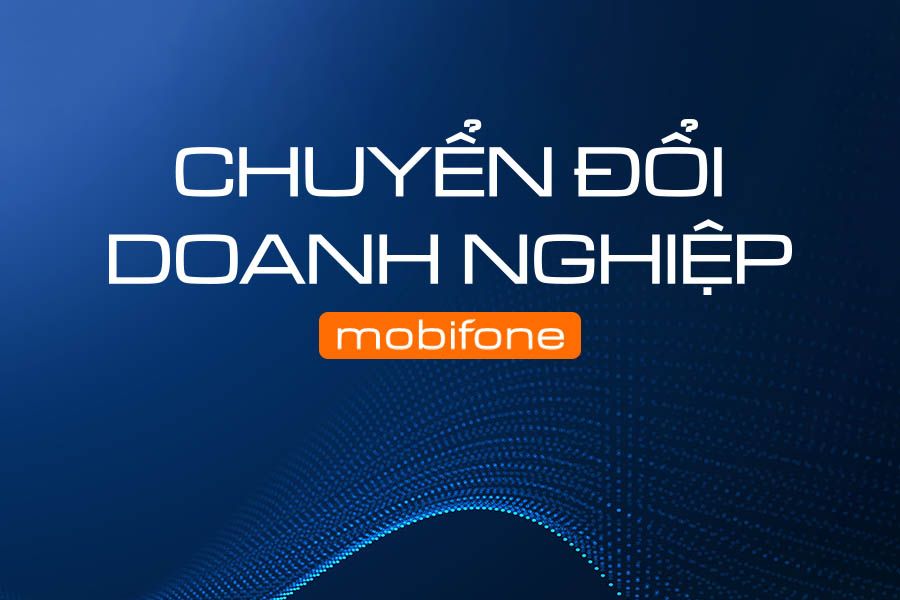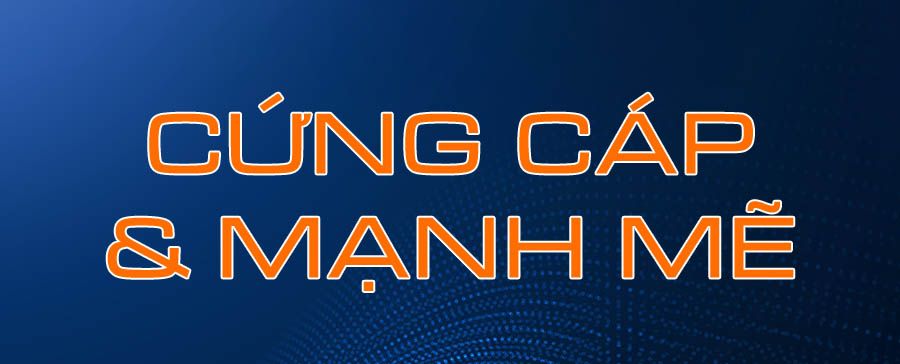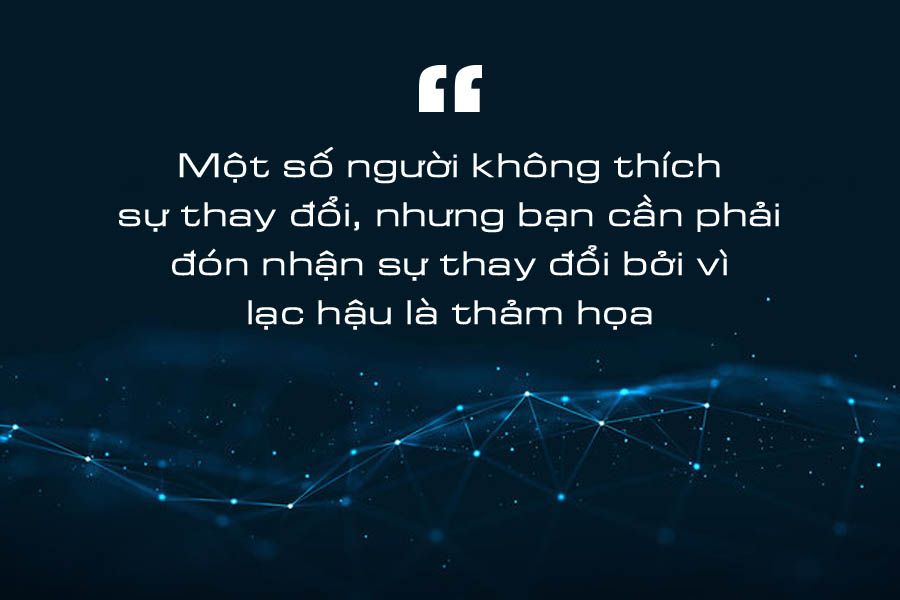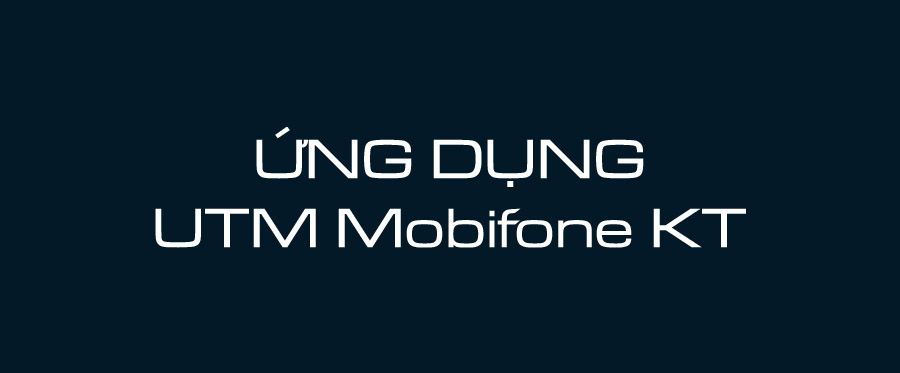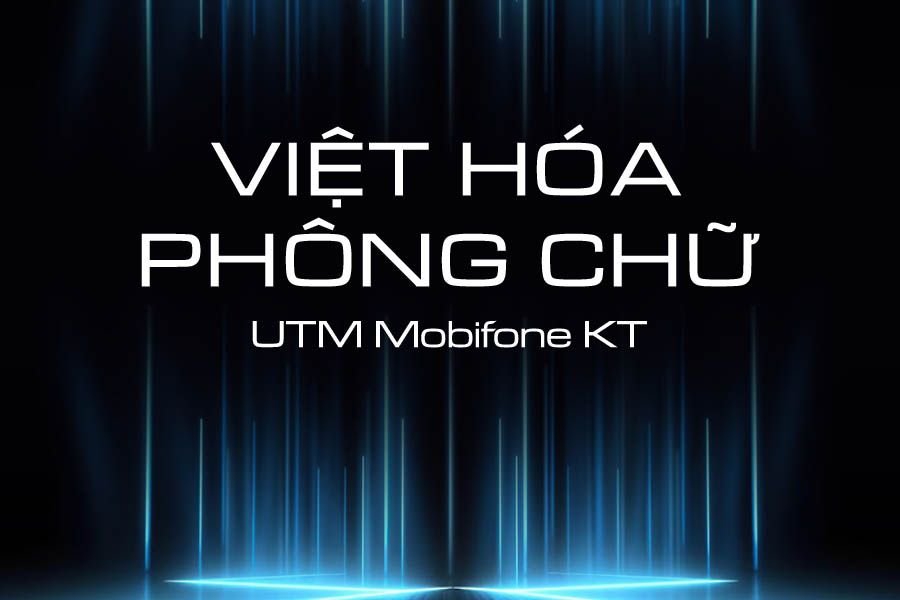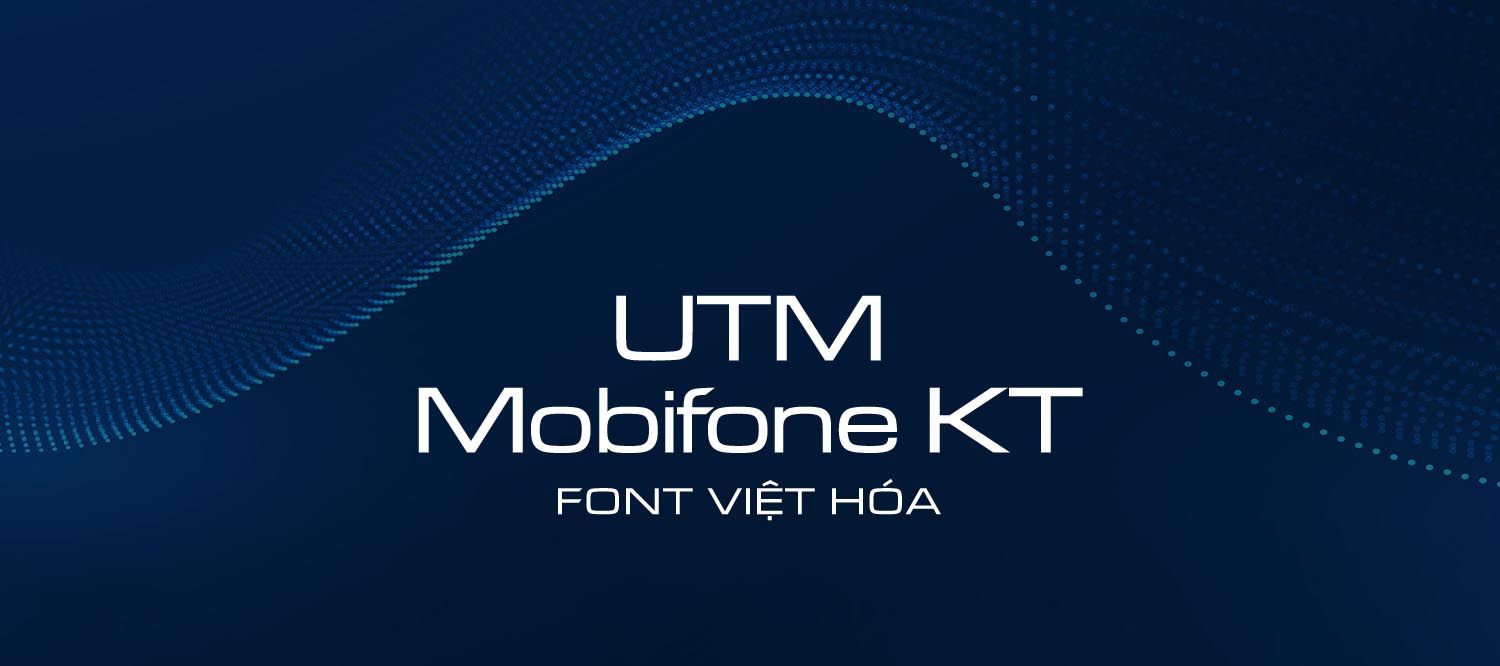
![[Tải Xuống] Font UTM Mobifone KT Cứng Cáp, Mạnh Mẽ & Hiện Đại](https://cdn.s99.vn//cloud/TCaD8aATd7PT8Ugo.jpeg)
Font UTM Mobifone KT là một kiểu chữ không chân (sans-serif) hiện đại, được Việt hóa bởi nhóm Urban Type Management (UTM) – đơn vị tiên phong trong việc Việt hóa font cho thương hiệu tại Việt Nam. Đây là bộ font từng xuất hiện trong bộ nhận diện của Mobifone, thể hiện tinh thần cứng cáp, mạnh mẽ và chuyên nghiệp – đúng với hình ảnh mà một tập đoàn viễn thông lớn muốn truyền tải.
Font UTM Mobifone KT sở hữu cấu trúc chữ không chân, mang đậm tính hiện đại và tối giản. Tuy nhiên, điều làm nên khác biệt chính là độ cứng cáp trong từng đường nét – các ký tự vuông vức, chắc chắn, không rườm rà nhưng vẫn dễ nhìn và đầy tính nhận diện. Sự mạnh mẽ này khiến font trở nên lý tưởng cho các thương hiệu công nghệ, tài chính, viễn thông và doanh nghiệp chuyên nghiệp.
Nhờ thiết kế hài hòa về khoảng cách chữ và tỷ lệ chiều cao, font UTM Mobifone KT luôn giữ được sự rõ ràng, sắc nét dù sử dụng trên màn hình số hay bản in. Dù là tiêu đề lớn hay body text nhỏ, font vẫn mang lại cảm giác dễ đọc, không bị vỡ chữ hay gây rối mắt.
Bộ font được Việt hóa hoàn chỉnh, hỗ trợ đầy đủ dấu và ký tự đặc biệt trong tiếng Việt. Các dấu thanh được thiết kế cân đối với thân chữ, đảm bảo sự đồng bộ thẩm mỹ – rất cần thiết trong thiết kế thương hiệu hoặc các sản phẩm truyền thông nội địa.
Không đơn thuần là một font đẹp, UTM Mobifone KT còn mang tính ứng dụng thương hiệu cao. Với sự kết hợp giữa phong cách hiện đại và độ cứng cáp đặc trưng, font tạo dựng được hình ảnh tin cậy, chuyên nghiệp và mạnh mẽ cho doanh nghiệp. Đây cũng chính là lý do font từng được lựa chọn trong hệ thống nhận diện thương hiệu của Mobifone.
Từ logo, biển hiệu, slide thuyết trình đến giao diện UI/UX, font UTM Mobifone KT đều phát huy được sức mạnh. Nó đủ tinh tế để làm tiêu đề nổi bật, nhưng cũng đủ gọn gàng, mạch lạc để sử dụng làm văn bản nội dung. Một lựa chọn toàn diện cho cả designer và doanh nghiệp.
Với thiết kế cứng cáp, mạnh mẽ và độ rõ ràng cao, font UTM Mobifone KT lý tưởng cho nhiều lĩnh vực thiết kế chuyên nghiệp:
Phù hợp để thiết kế logo, slogan, hồ sơ năng lực cho các doanh nghiệp viễn thông, công nghệ và ngân hàng. Font tạo cảm giác chuyên nghiệp, đáng tin cậy, phù hợp với hình ảnh thương hiệu lớn.
Font có khả năng hiển thị tốt trên mọi thiết bị, thích hợp cho thiết kế UI/UX, ứng dụng mobile, trang web doanh nghiệp và hệ thống nội bộ, đảm bảo nội dung dễ đọc, mạch lạc.
Các nét chữ rõ ràng, gọn gàng giúp font dễ ứng dụng trong biển quảng cáo, card visit, profile công ty và các tài liệu in ấn, tăng khả năng ghi nhớ thương hiệu.